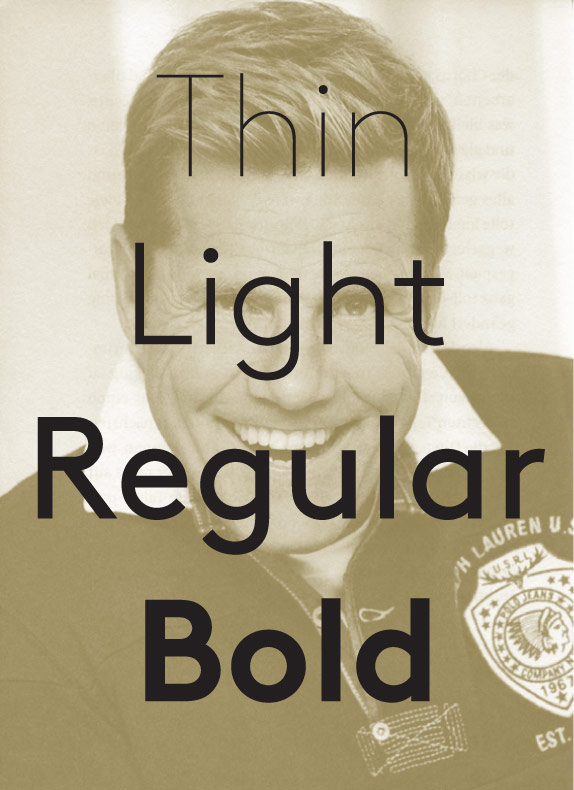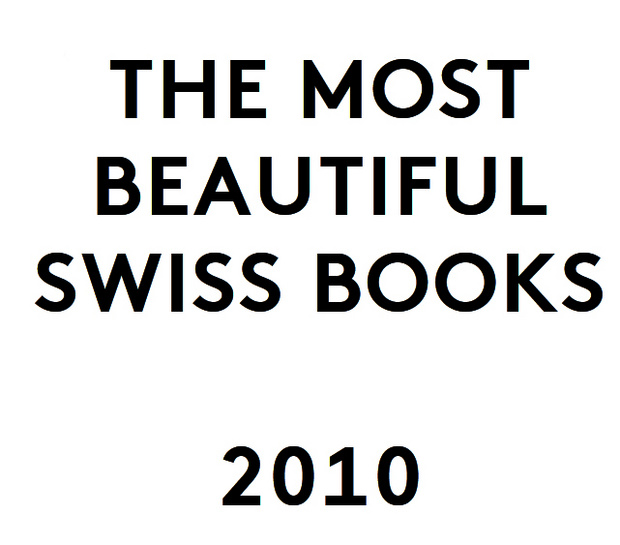
Welche Schrift verwendet der Swiss Design Award?
Die Schrift sieht ähnlich aus wie Futura, Underground oder Neuzeit, ist aber doch merklich moderner, die gesucht Schrift wird auch auf Mirko Borsches Website verwendet.
What the Font und Identyfont helfen mir wiedermal nicht mehr weiter...
hier gefunden:
warum nutzen die dieter bohlen als werbung für den font?
Ich war eben zufällig auch auf der Lineto-Seite und habe mich dasselbe gefragt ... :-?
... wirkt aber, zumindest hier, schon mal.;-)
Die Auszeichnung der LL Brown hat einen leicht faden Beigeschmack da Cornel Windlin, der in der Jury saß, gleichzeitig auch Chef von Lineto ist und der Release wohl schon vor der Auszeichnung fest stand. Ich mag die Schrift trotzdem ...
Ist doch sonnenklar, warum die den Bohlen als Markenbotschafter für die LL Brown benutzen. Bohlen ist sowas wie The Hardest Working Man In Show Business, ne!? Wenigstens in Deutschland. Und damit der deutsche Jaaaaaames ... BROWN! Also mir leuchtet das total ein.